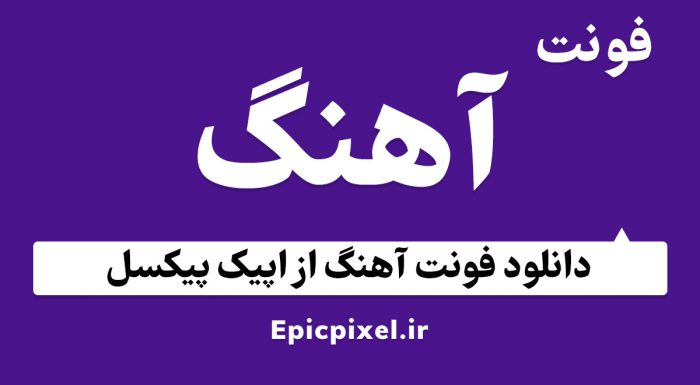
فونت آهنگ، با الهام از فونت های مطبوعاتی ایرانی و خوشنویسی نسخ و ثلث، حس و حالی نوستالژیک و در عین حال مدرن را به مخاطب القا می کند. این فونت که بازسازی شده ی فونت فرهنگ است، با تغییراتی هوشمندانه، خوانایی و جذابیت بصری را به اوج رسانده. فونت آهنگ شارپ، نسخه ی اولیه ی این فونت بوده که با تغییراتی مانند تخت کردن و کاهش کنتراست، به فونت آهنگ اصلی تبدیل شده است. این ویژگی ها باعث می شوند متن ها چشم نوازتر و حرفه ای تر به نظر برسند.
یکی از ویژگی های برجسته ی فونت آهنگ، داشتن حروف جایگزین است. این حروف که شامل مواردی مانند ﮧ، ﮩ (مدل نستعلیق) و ے معکوس می شوند، در واقع حروف زبان اردو هستند. از آنجا که فونت آهنگ این حروف را در خود جای داده، امکان استفاده از آن ها در کیبورد فارسی نیز فراهم شده و به کاربران اجازه می دهد تا تنوع بیشتری در نوشته های خود ایجاد کنند. این ویژگی به خصوص برای طراحان گرافیک و کسانی که به دنبال ایجاد آثار هنری با تایپوگرافی خاص هستند، بسیار ارزشمند است.
اگر به دنبال فونتی هستید که هم اصالت داشته باشد و هم مدرن به نظر برسد، فونت آهنگ انتخابی ایده آل است. این فونت با ویژگی های منحصر به فرد خود، به نوشته های شما جلوه ای خاص می بخشد و آن ها را از سایر متن ها متمایز می کند.